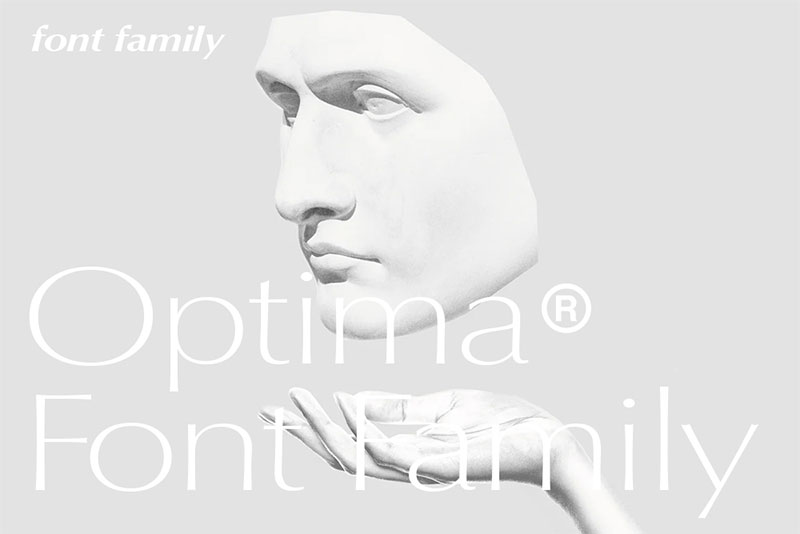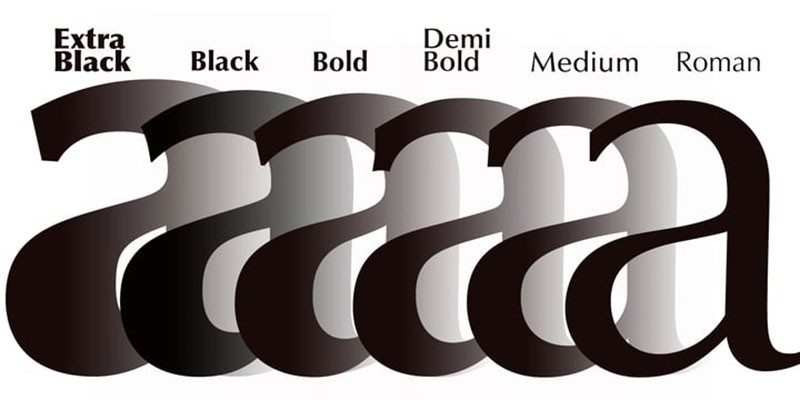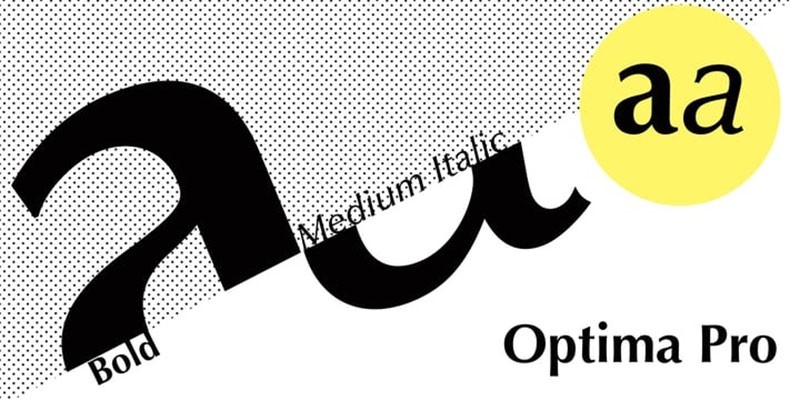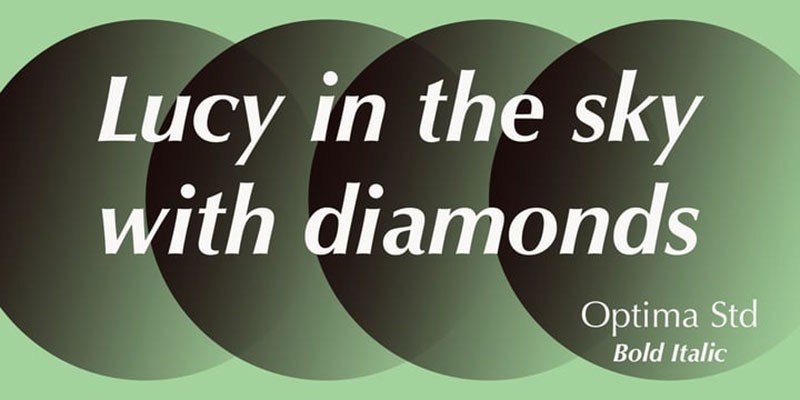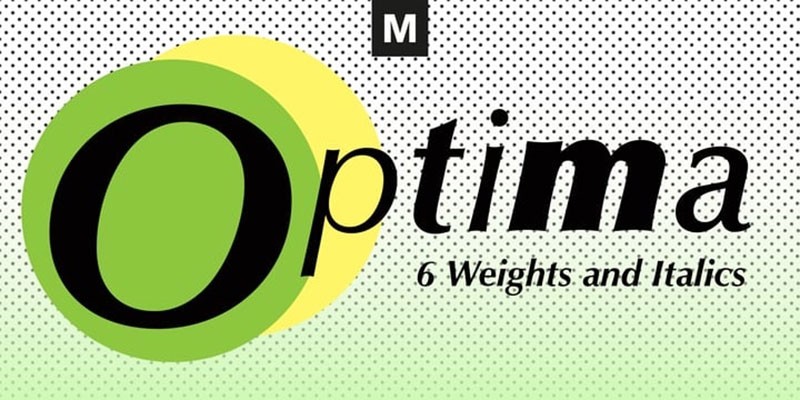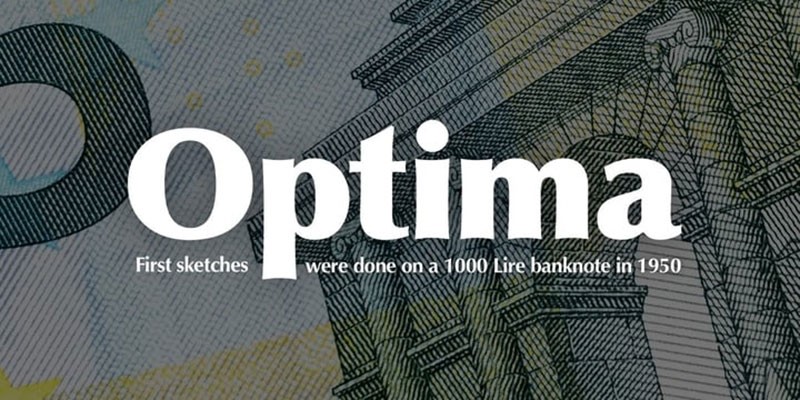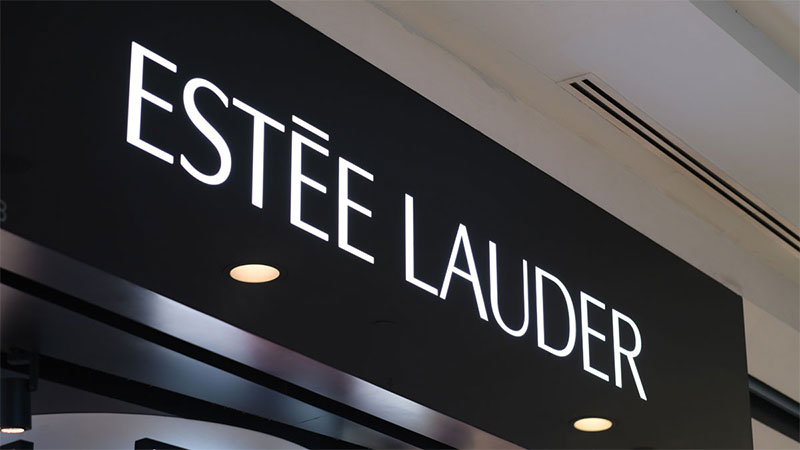
Optima时尚大牌英文字体完整版
Optima是一款典雅、现代和多功能的无衬线字体,由德国设计师 Hermann Zapf 在1952年创建。它具有独特的典雅外观和现代感,结合了圆润和几何形状,使其在印刷和设计中广受欢迎。
Optima的字母形状相对较宽,高度适中,具有大量的字母间距,使其易于阅读。该字体具有33种不同字重,可用于各种设计项目,如书籍封面、海报、广告、徽标等。Optima还是许多公司品牌标志和标识的常用字体之一,其现代感和易读性使其成为广告和设计界的常见选择。